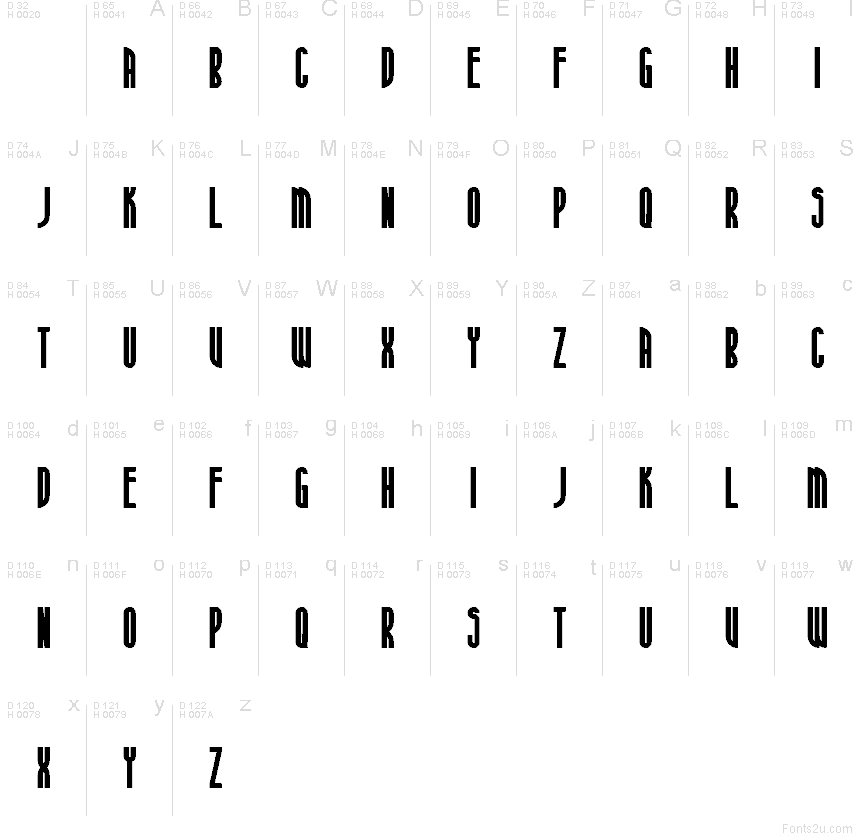
Retro Famous Elegant od Vladimir Nikolic je bezplatné Art Deco display písmo s vysokým a štíhlym rytmom, ktorý pripomína staré filmové nápisy a hlavičky vtedajších časopisov. Písmená pôsobia elegantne a vzpriamene, postavené na širokých zvislých ťahoch a čistých geometrických výrezoch. To dodáva písmu vycibrený vzhľad 20. a 30. rokov minulého storočia bez toho, aby skĺzlo k zbytočnému zdobeniu.
Skvele sa hodí na titulky plagátov, obaly, knižné obálky, koktailové menu či značky, kde potrebujete, aby dobový hlas pôsobil čisto a kontrolovane. Ako bezplatné písmo na krátke nadpisy, titulné kartičky alebo monogramy funguje najlepšie vtedy, keď necháte tieto pretiahnuté tvary rozprávať samé za seba.